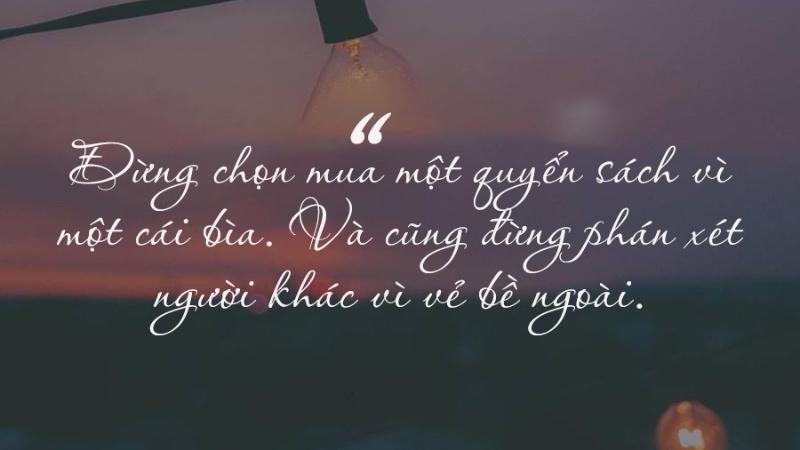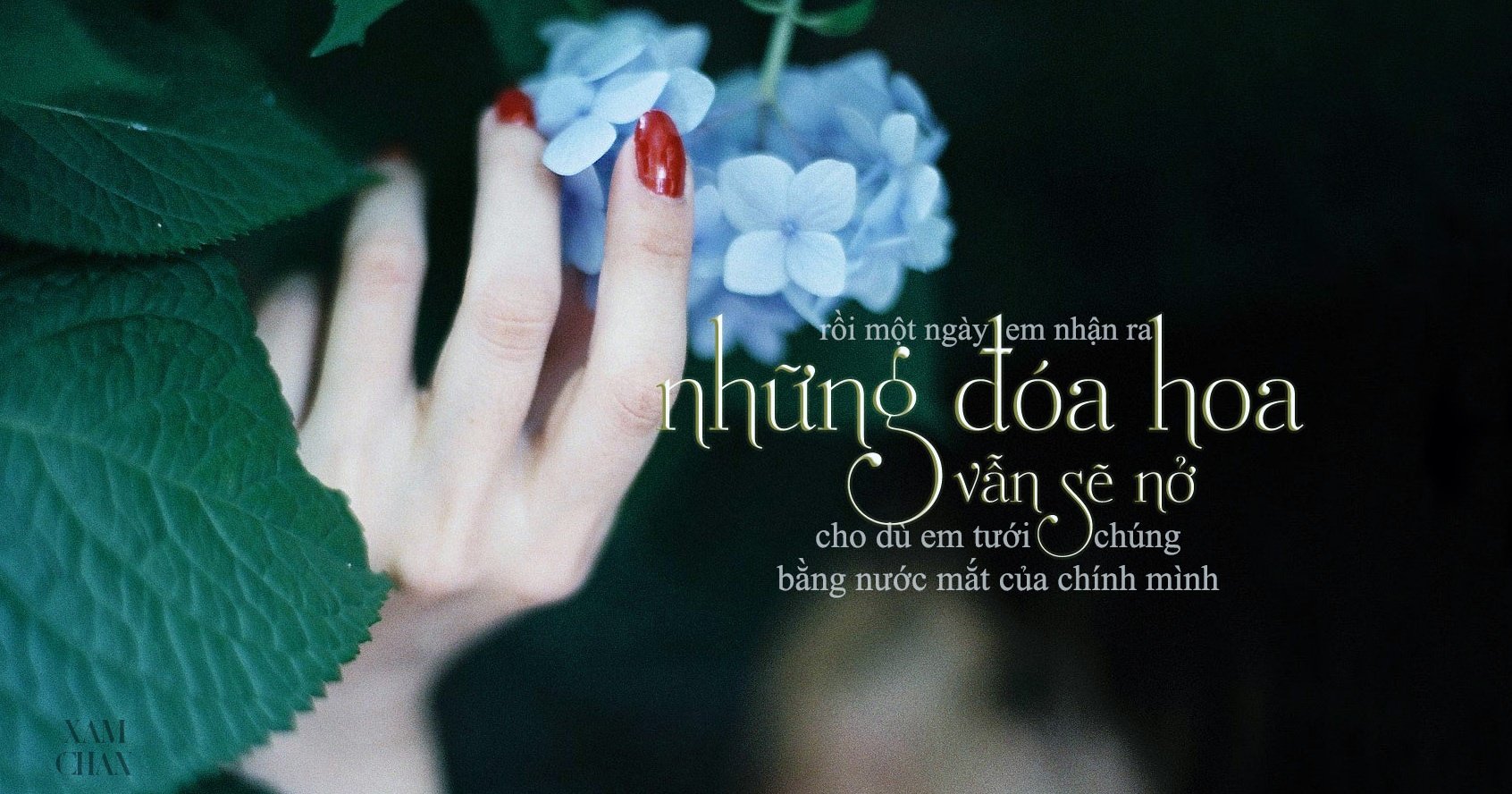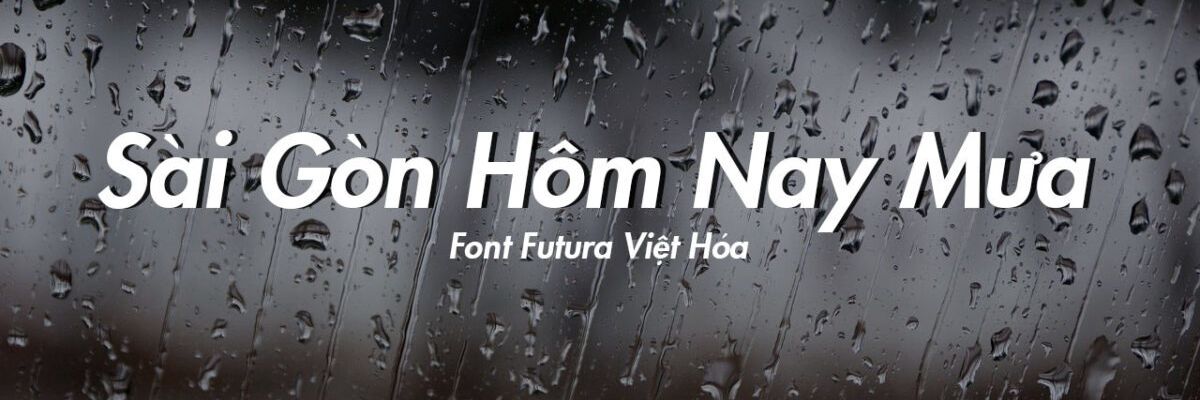
Những kiểu Font Việt hóa đẹp, đặc sắc mà bạn không nên bỏ qua
Font Việt hóa là gì?
Font Việt hóa là các kiểu chữ được điều chỉnh và tùy biến từ font gốc quốc tế để có thể sử dụng trọn vẹn trong tiếng Việt. Đặc điểm nổi bật của font Việt hóa là khả năng hiển thị đầy đủ các dấu thanh và ký tự đặc trưng như "ă," "â," "đ," "ê," "ô," và các tổ hợp dấu câu phức tạp. Quá trình Việt hóa không chỉ đơn thuần là thêm dấu mà còn phải đảm bảo sự hài hòa giữa các ký tự, giữ nguyên phong cách ban đầu của font. Điều này giúp font trở nên tự nhiên hơn khi sử dụng trong các thiết kế tiếng Việt, không gây cảm giác lạ lẫm hay mất cân đối.
Đặc điểm của Font Việt hóa
Một điểm khác biệt quan trọng của font Việt hóa so với các font gốc là sự tinh chỉnh cẩn thận để hỗ trợ tốt nhất cho tiếng Việt. Các dấu câu, đặc biệt là dấu thanh, được đặt ở vị trí cân đối để không làm rối mắt hoặc mất đi sự liền mạch trong thiết kế. Ngoài ra, kích thước và độ dày của các ký tự thường được tùy chỉnh để giữ lại vẻ đẹp nguyên bản của font, nhưng đồng thời cũng đảm bảo rằng chúng phù hợp với cách viết và đọc của người Việt.
Hơn nữa, font Việt hóa còn giúp giải quyết vấn đề phổ biến khi dùng font quốc tế – sự thiếu hụt các ký tự đặc trưng tiếng Việt. Điều này đặc biệt quan trọng đối với những người làm thiết kế chuyên nghiệp hoặc các dự án cần sự chỉn chu trong từng chi tiết. Một font Việt hóa tốt không chỉ đơn giản là đầy đủ ký tự mà còn cần đảm bảo tính đồng nhất về kiểu dáng và sự hài hòa trong toàn bộ bố cục.
Việc sử dụng font Việt hóa không chỉ dừng lại ở yếu tố kỹ thuật mà còn thể hiện sự tôn trọng ngôn ngữ và văn hóa bản địa. Đây chính là lý do khiến ngày càng nhiều nhà thiết kế tìm đến các font Việt hóa, không chỉ để hoàn thiện sản phẩm mà còn để mang lại giá trị nghệ thuật và cảm xúc đậm chất Việt trong từng thiết kế.
Top 7 Font việt hóa đẹp dành cho dân thiết kế
Lato (Lato trong tiếng Ba Lan có nghĩa là mùa hè) là font chữ thuộc họ Sans serif được Łukasz Dziedzic thiết kế vào mùa hè năm 2010. Sau đó đã được Google hỗ trợ xuất bản theo Giấy phép Phông chữ Mở bởi ty Poland.
Font chữ việt Hóa Lato với những đường nét tròn nhẹ trên chữ cái mang lại cảm giác ấm áp của mùa hè nhưng không kém phần sang trọng và nghiêm khắc nhờ vào thiết kế cổ điển.
Font iCielBC Downtown
Font việt hóa này được thiết kế bởi một bạn nữ Hà Nội, lấy cảm hứng từ những bảng hiệu được vẽ tay, những hình ảnh bình dị, màu sắc đơn giản từ thời bao cấp. Tuy nhiên font này bạn chỉ nên tải về dùng với mục đích cá nhân, nếu dùng để thiết kế thì bạn nên mua bản quyền nhé.
Font SVN-Product Sans
Đây là font chữ Việt Hóa được thiết kế bởi Google Inc nhằm mục đích xây dựng thương hiệu cho riêng mình và được dùng để thay thế logo Google vào tháng 9 năm 2015. Bạn sẽ bắt gặp font này xuất hiện trên hầu hết các ứng dụng của Google.
Font Futura
Futura là một kiểu chữ sans serif được thiết kế bởi Paul Renner và được phát hành vào năm 1927, dựa trên các hình dạng hình học, đặc biệt là hình tròn, giống với tinh thần của phong cách thiết kế Bauhaus thời kỳ đó. Dù đã ra đời từ rất lâu nhưng tính đến thời điểm hiện tại thì đây vẫn là một trong những font chữ được tìm kiếm phổ biến nhất.
Font Bìa Sách Xưa
Font chữ Bìa Sách Xưa được thiết kế bởi Tống Văn Diệp, ông đã lấy cảm hứng từ những biển quảng cáo, trên những bìa sách cũ lâu đời của Việt Nam vào những năm 1980 của thế kỉ trước. Với đường nét ngang dày và đường nét thẳng dọc mảnh khảnh của từng con chữ gợi lại cảm giác hoài cổ, hoài niệm cho người đọc.
Font Bon Foyage
Font chữ việt hóa NVN Bon Foyage thuộc họ serif thư pháp theo phong cách hiện đại, phù hợp với nhiều chủ đề thiết kế bao gồm thời trang, tạp chí, logo, thương hiệu, nhiếp ảnh, lời mời, lời mời đám cưới, trích dẫn, tiêu đề blog, áp phích, quảng cáo, bưu thiếp, sách, trang web.
Font SVN-TheUntold Story
SVN-TheUntold Story là font chữ viết tay theo phong cách vui nhộn, tinh nghịch. Font chữ này hoàn hảo cho các ấn phẩm thiết kế bao gồm: tờ rơi, thiệp chúc mừng, bao bì sản phẩm, bìa sách, bìa album, thiết kế hình ảnh trong may mặc.